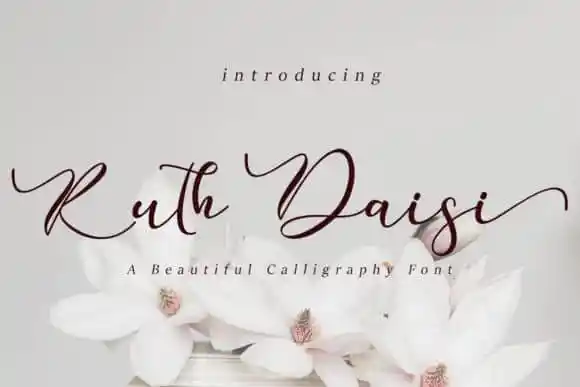
Ruth Daisi Calligraphy Font – Download Grátis
A Ruth Daisi Calligraphy Font é uma escolha perfeita para quem deseja dar vida a suas criações com um estilo elegante e romântico. Este recurso de escrita decorativa oferece movimentos suaves e delicados, bem como ligaturas belas, letras alternativas e espigões que adicionam profundidade aos seus trabalhos. Com suas letras distintas e perfeitamente redondas, a Ruth Daisi se destaca como uma obra-prima do design gráfico. Esta fonte é tão versátil que pode ser usada em um vasto conjunto de projetos: desde cartões personalizados até editoriais jornalísticos ou revistas. Se você está buscando criar designs impressionantes e diversificados, a Ruth Daisi Calligraphy Font é o seu selo definitivo.